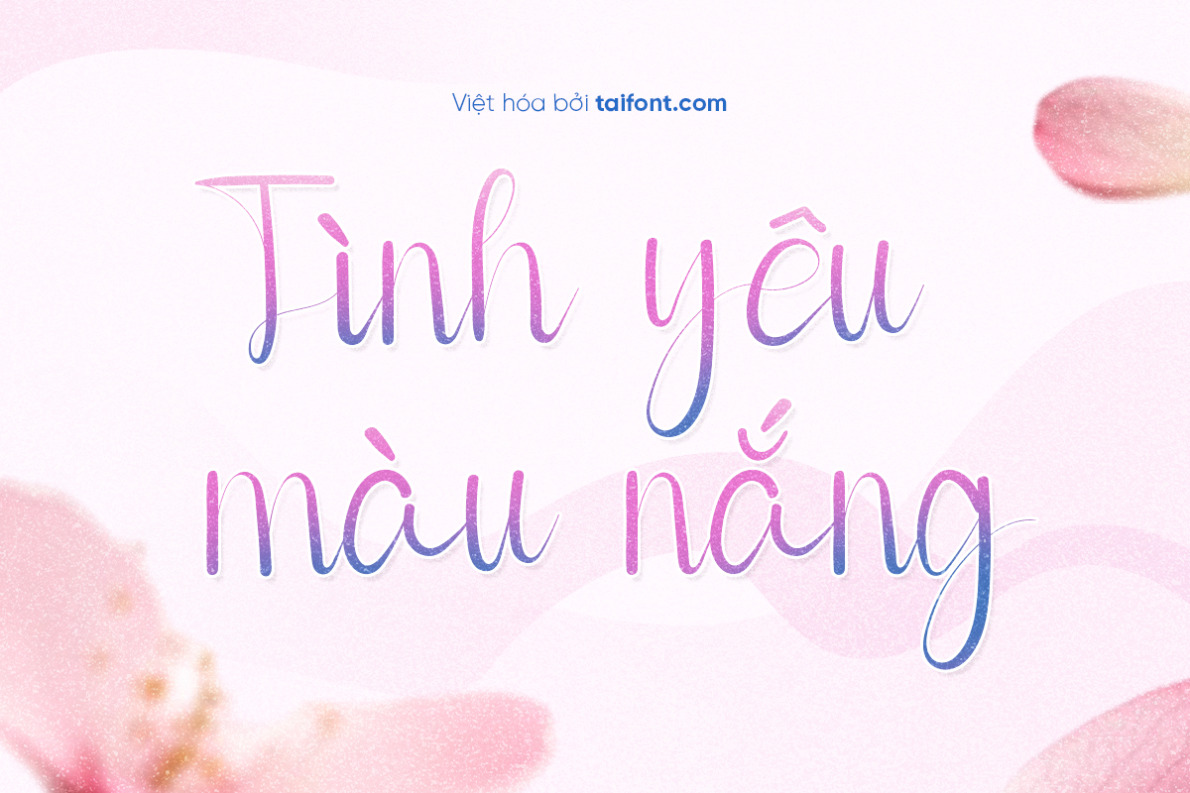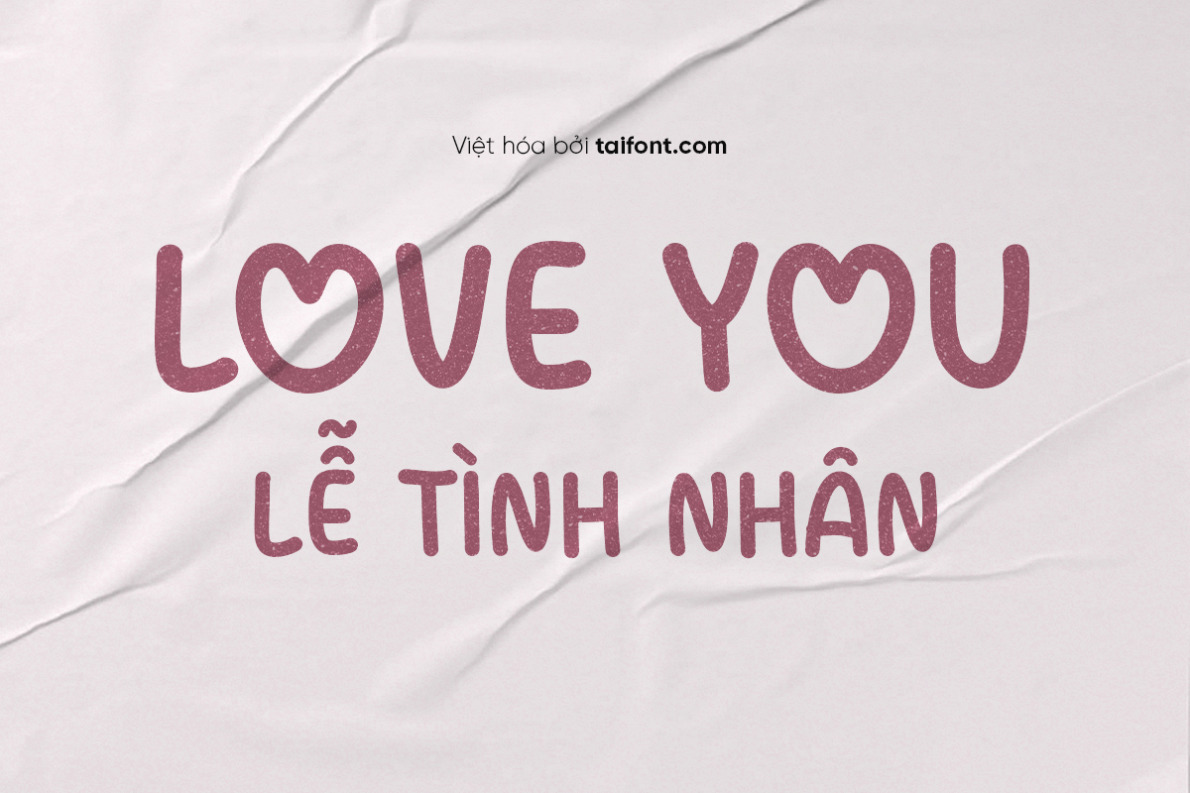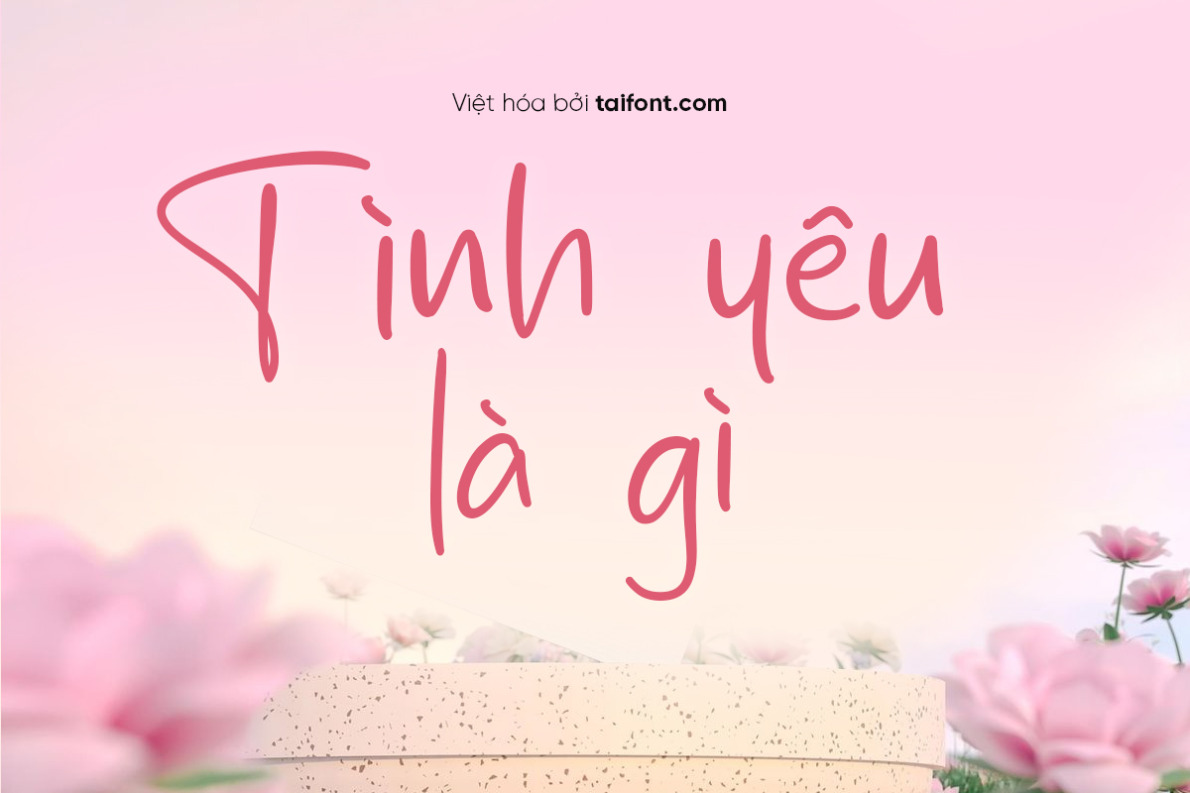
Top 5 Font chữ tình yêu Việt hóa valentine
Top 5 Font chữ tình yêu Việt hóa valentine là những font chữ phù hợp cho thiết kế dịp lễ tình nhân
Top 1: Font Việt hóa TF Valentine Girls
Top 2: Font việt hoá MJ Charming Valentines
Top 3: Font Việt hóa TF Love House
Top 4: Font việt hoá MJ LoveLy Love
Top 5: Font Việt hóa TF Beautiful Sunflower